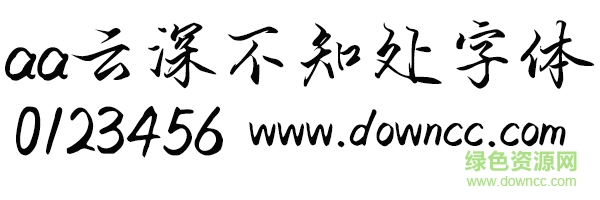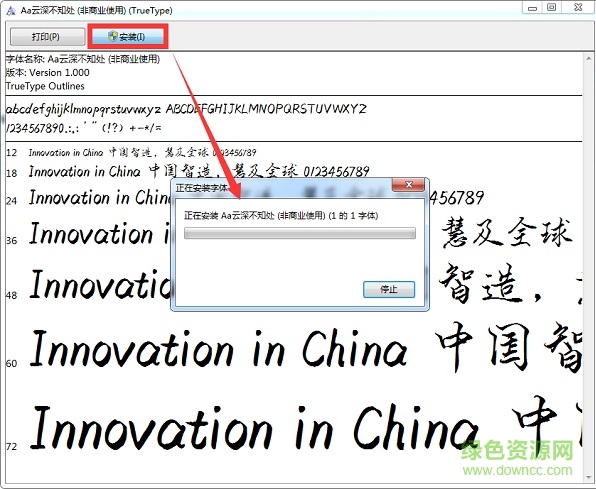
aa云深不知處字體是一個類似于鋼筆字的字體資源,和手寫的鋼筆字體很像。這款字體也被很多智能手機用戶喜愛。今天為大家?guī)淼碾娔X端字體程序可以在word等軟件中直接打開使用哦!
aa云深不知處字體ttf字體清晰明朗,字形靈動飄逸,適合應用于藝術(shù)設(shè)計、平面設(shè)計、網(wǎng)頁設(shè)計!喜歡這款字體的朋友快來綠色資源網(wǎng)下載吧!